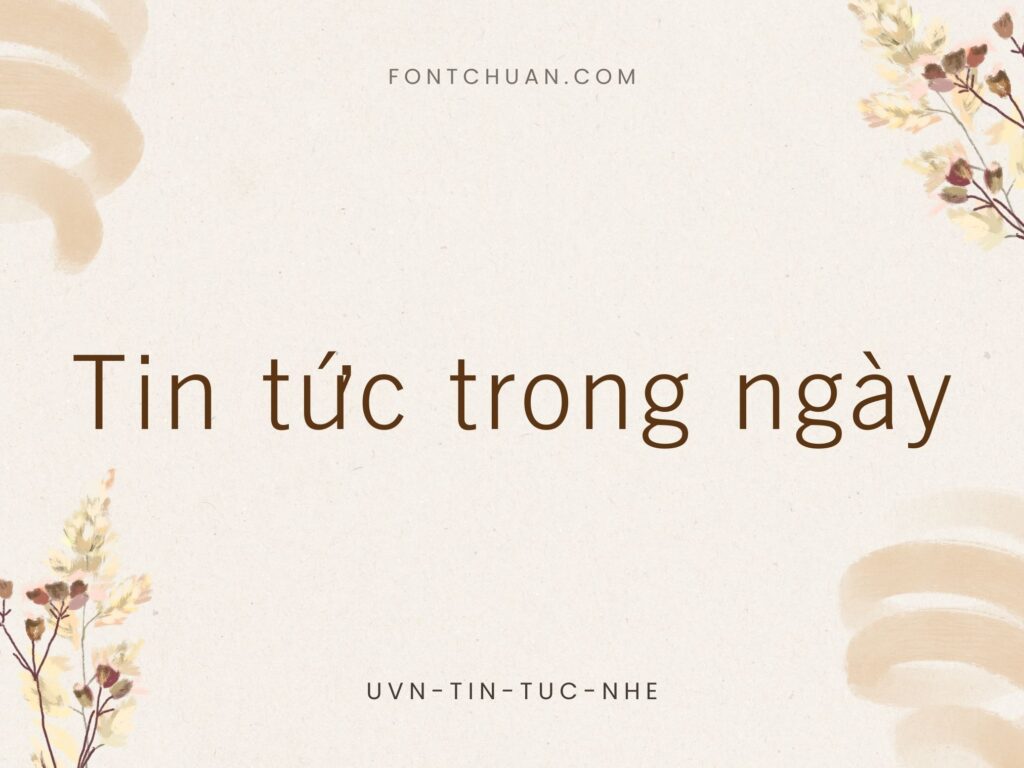
Font UVN Tin Tuc Nhe Việt Hóa
UVN Tin Tức Nhẹ là phiên bản nhẹ hơn của font UVN Tin Tức, mang phong cách sans-serif hiện đại và tối giản, lý tưởng cho các thiết kế cần sự thanh thoát và nhấn mạnh tính thông tin. Thuộc bộ font UVN phổ biến tại Việt Nam, kiểu chữ này được cộng đồng thiết kế ưa chuộng nhờ khả năng thích ứng cao trong nhiều định dạng và nội dung khác nhau. Khi kết hợp với Font Monospace, UVN Tin Tức Nhẹ có thể tạo ra sự đối lập thú vị giữa sự tinh gọn và tính kỹ thuật, giúp thiết kế trở nên chuyên nghiệp và dễ đọc hơn. Font này chỉ được sưu tầm và đăng bởi thành viên của Font Chuẩn, nhằm hỗ trợ người dùng có thêm sự lựa chọn phong phú và hiệu quả trong công việc thiết kế, trình bày ấn phẩm.
UVN Tin Tức Nhẹ có đường nét gọn gàng, tỷ lệ cân đối, độ dày mảnh giúp hiển thị tốt trên nền sáng và phù hợp với những thiết kế tinh tế như báo điện tử, ứng dụng di động, tạp chí số hay các slide thuyết trình. Với hình thức thân thiện và nhịp điệu thị giác ổn định, font phù hợp với các ngành như giáo dục, công nghệ, bất động sản và truyền thông. Đồng thời, nó cũng phát huy hiệu quả trong các sự kiện như ngày Nhà giáo, Tết, lễ hội hay dịp sinh nhật.